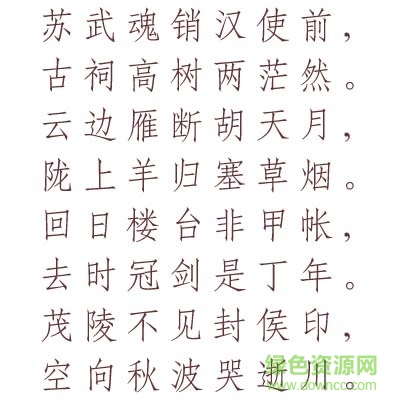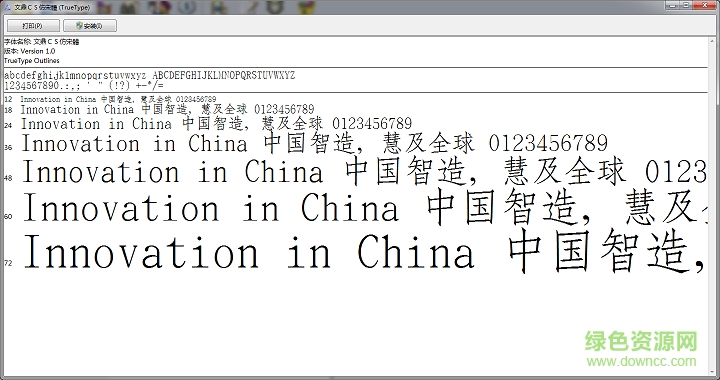
文鼎cs仿宋體是一款模仿宋體字創(chuàng)作而來(lái)的文鼎字體,完美繼承了宋體的特點(diǎn),宋體是現(xiàn)在資格最老的印刷字體,而且這個(gè)仿宋體深得其精髓,真有一種宋體的滄勁感,筆畫細(xì)膩,字形靈動(dòng)。趕快下載體驗(yàn)吧!
文鼎仿宋體,是一個(gè)陣容龐大的媒體體系。它的字體字型多種多樣,但使用起來(lái)往往容易擇選不當(dāng)或陷入盲目。本文以科學(xué)的態(tài)度和嚴(yán)謹(jǐn)?shù)睦碚摚^系統(tǒng)全面地論述了漢字媒體的字體造型特點(diǎn)與藝術(shù)風(fēng)格。以鮮明的觀點(diǎn)和新穎的思路,提出了五種風(fēng)格體系論,認(rèn)真強(qiáng)調(diào)和積極倡導(dǎo)發(fā)揮漢字字體形象藝術(shù)感染力的必要性,對(duì)正確、全面、合理地使用漢字字體,具有積極意義藝術(shù)化漢字,是我國(guó)報(bào)刊雜志編輯出版使用最多的文字。計(jì)算機(jī)字庫(kù)所列的漢字字體名目不下百種,最常用的類別目前主要有21種。其余只是點(diǎn)畫粗細(xì)上的差別,或取名有些差異。即便稍有形體上的變化,或無(wú)實(shí)質(zhì)性的不同,或不出其體系范圍。漢字庫(kù)的字體版本有國(guó)標(biāo)GB2312、微軟體、文鼎體、漢鼎體、漢儀體、華康體、方正體、長(zhǎng)城體、金山體、金橋體、創(chuàng)意體等多種。這些版本的字體,收納數(shù)量不一,種類相互參照或有部分雷同。但由于取材、審美或制版工藝的標(biāo)準(zhǔn)不同,字體模樣也不盡相同。使用者可以根據(jù)自己的想法和要求進(jìn)行擇選,不必強(qiáng)求一律。只是,必須認(rèn)識(shí)所要使用的字體,必須了解它的藝術(shù)特征。只有這樣,才能保證漢字字體使用的正確性和合理性。